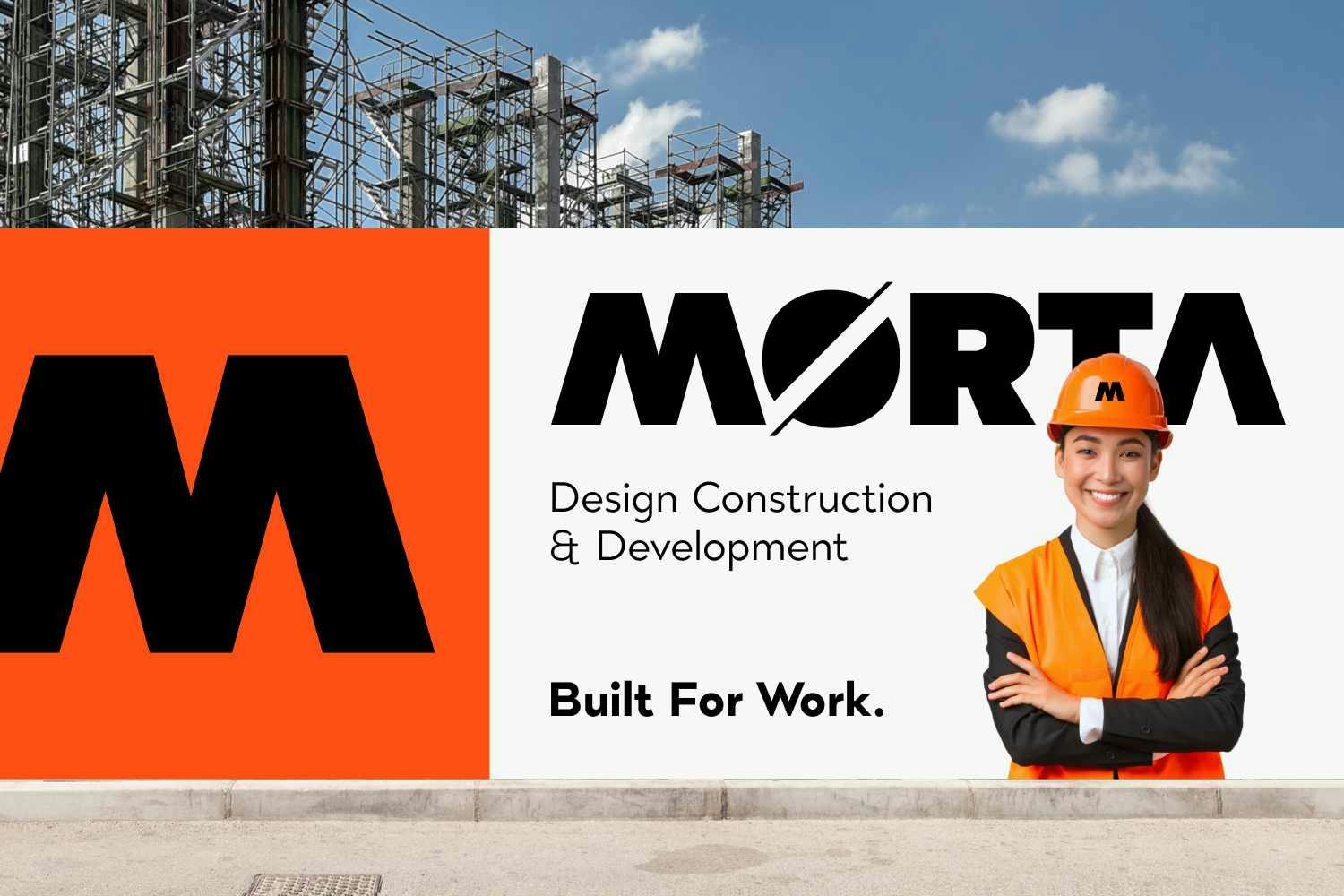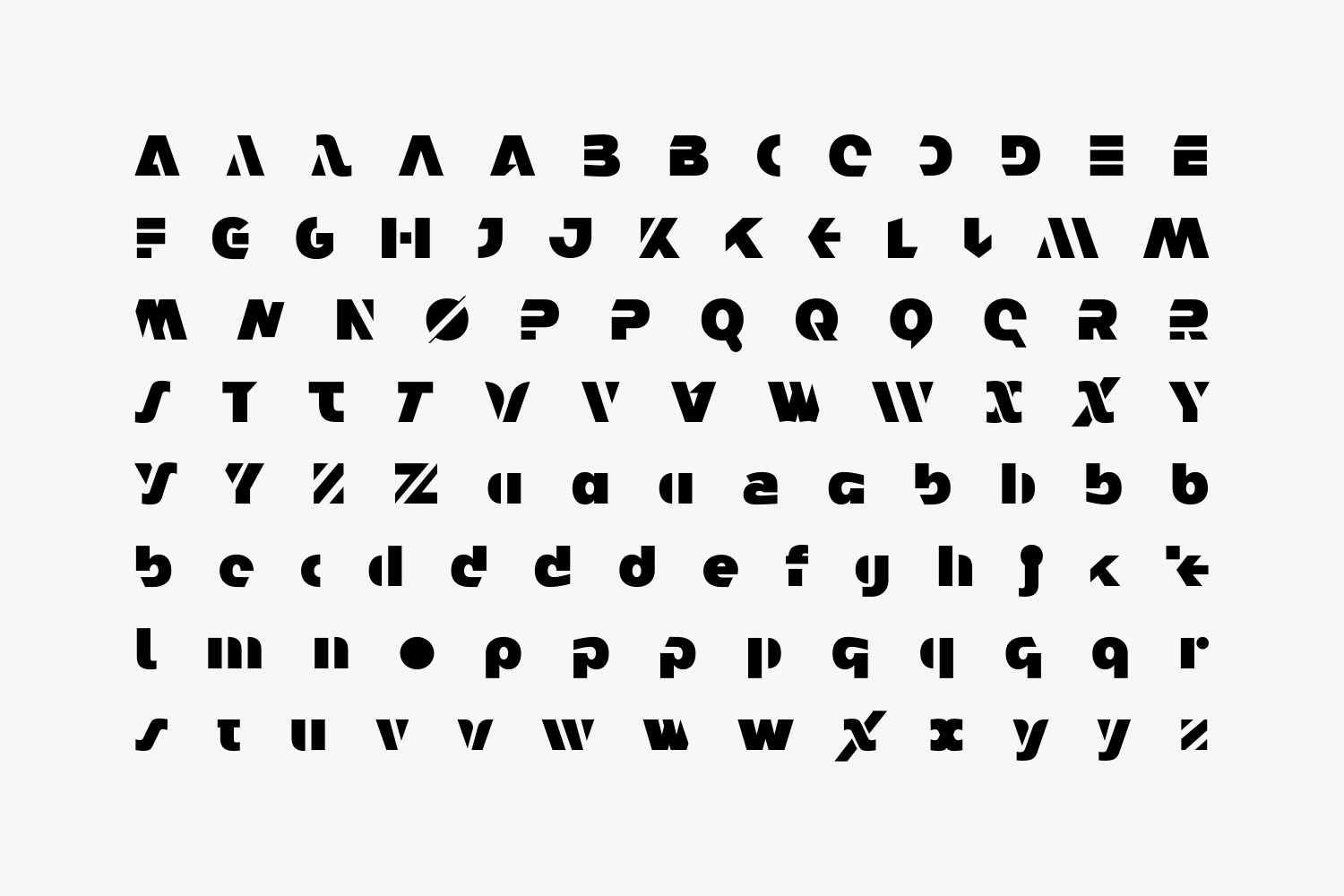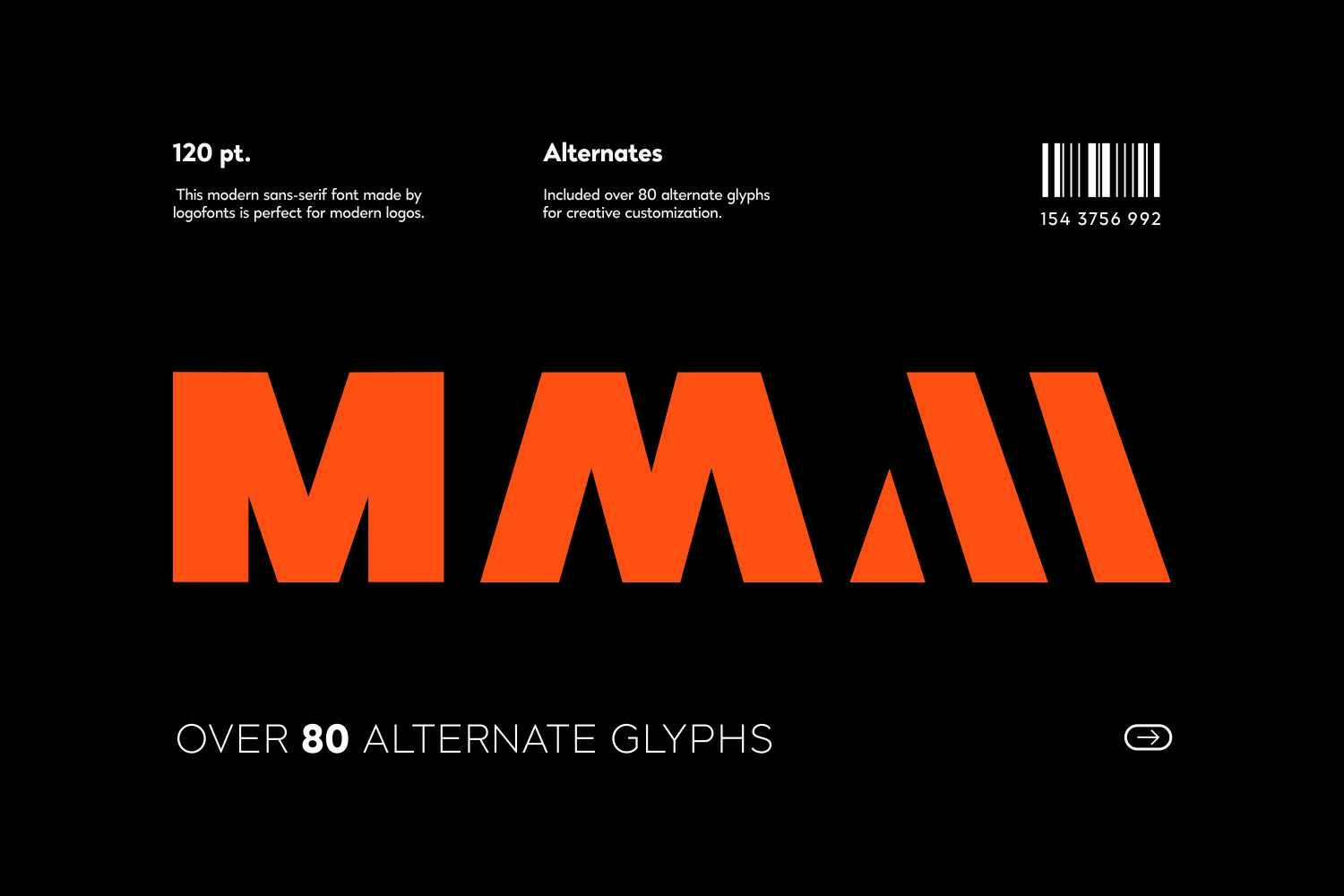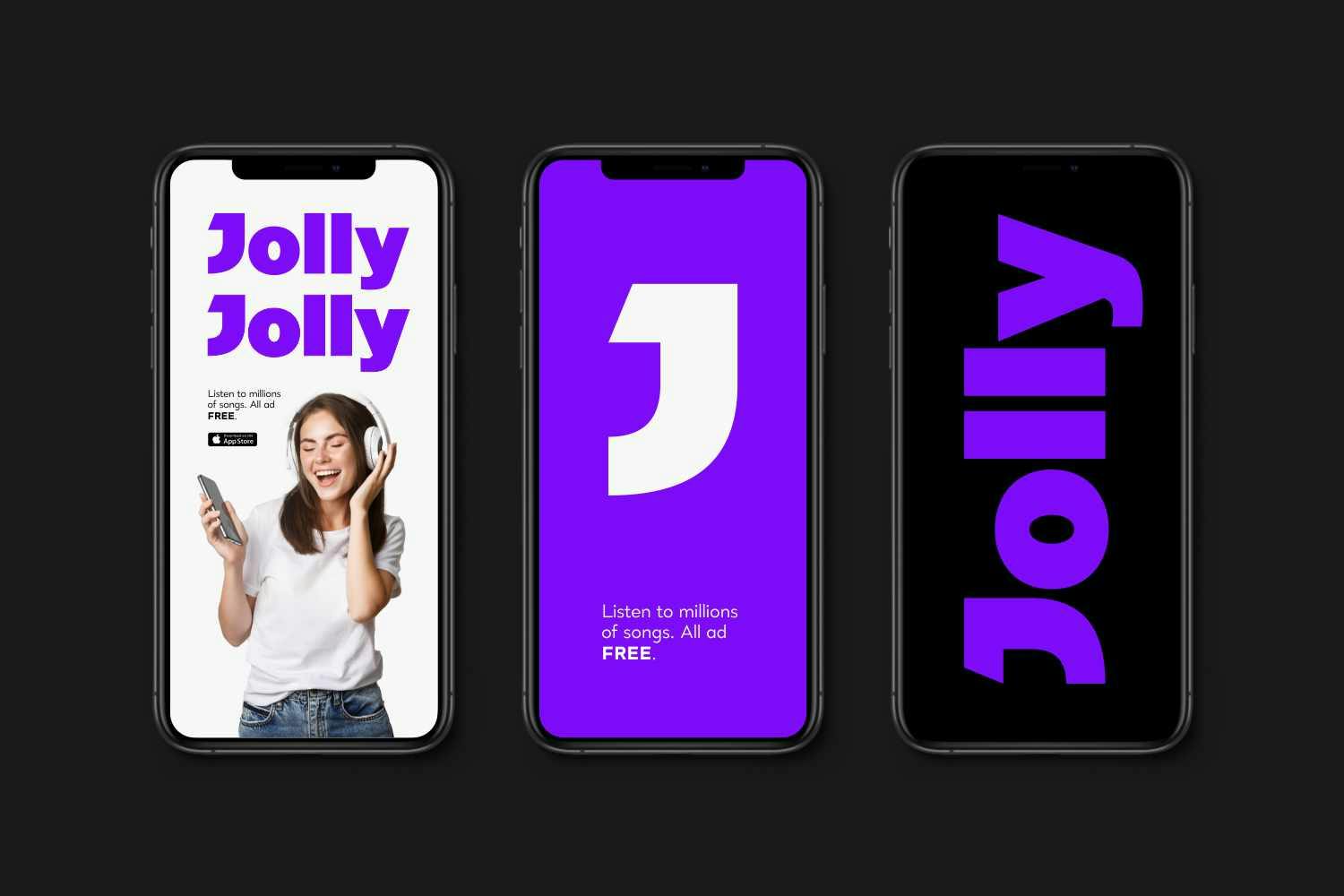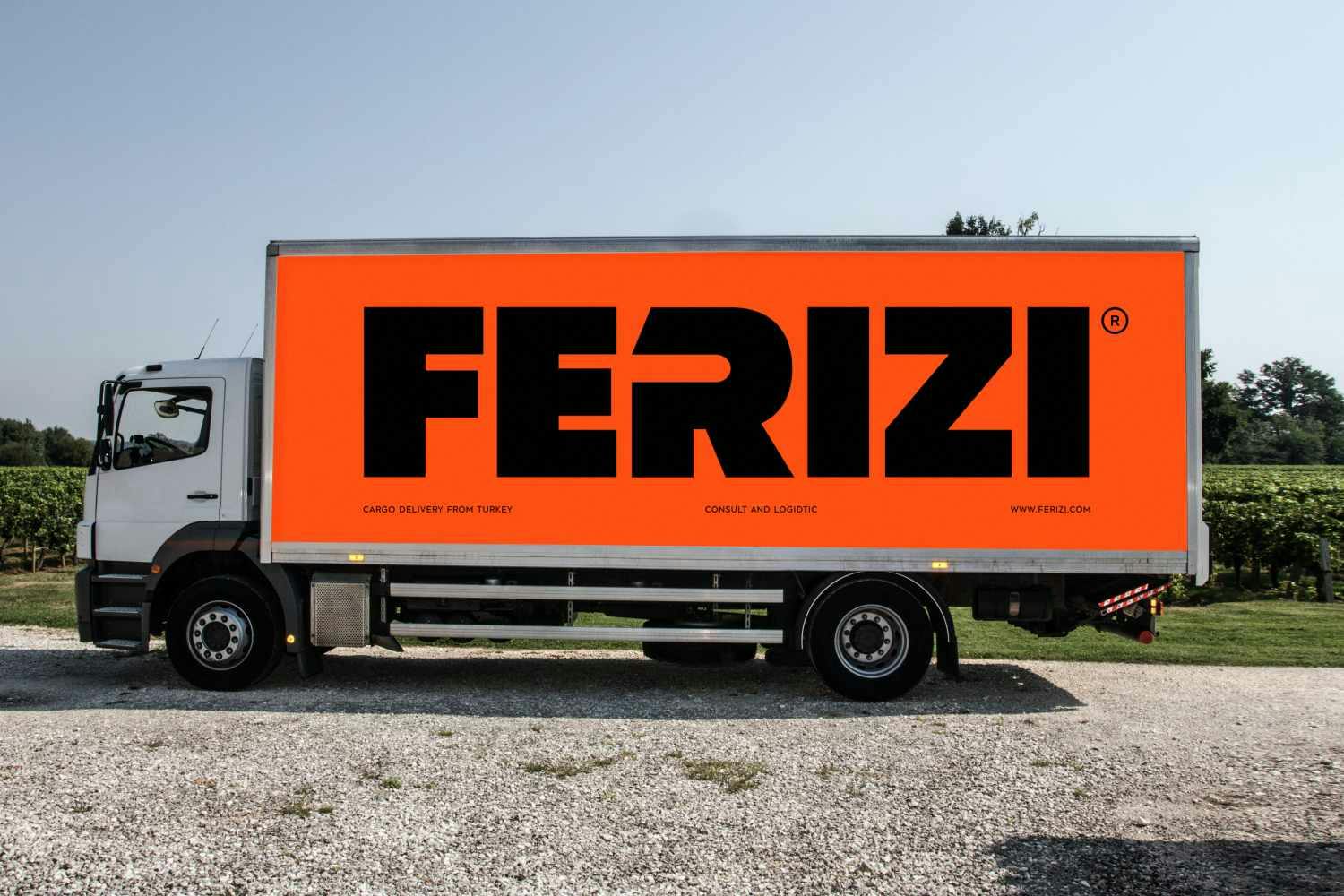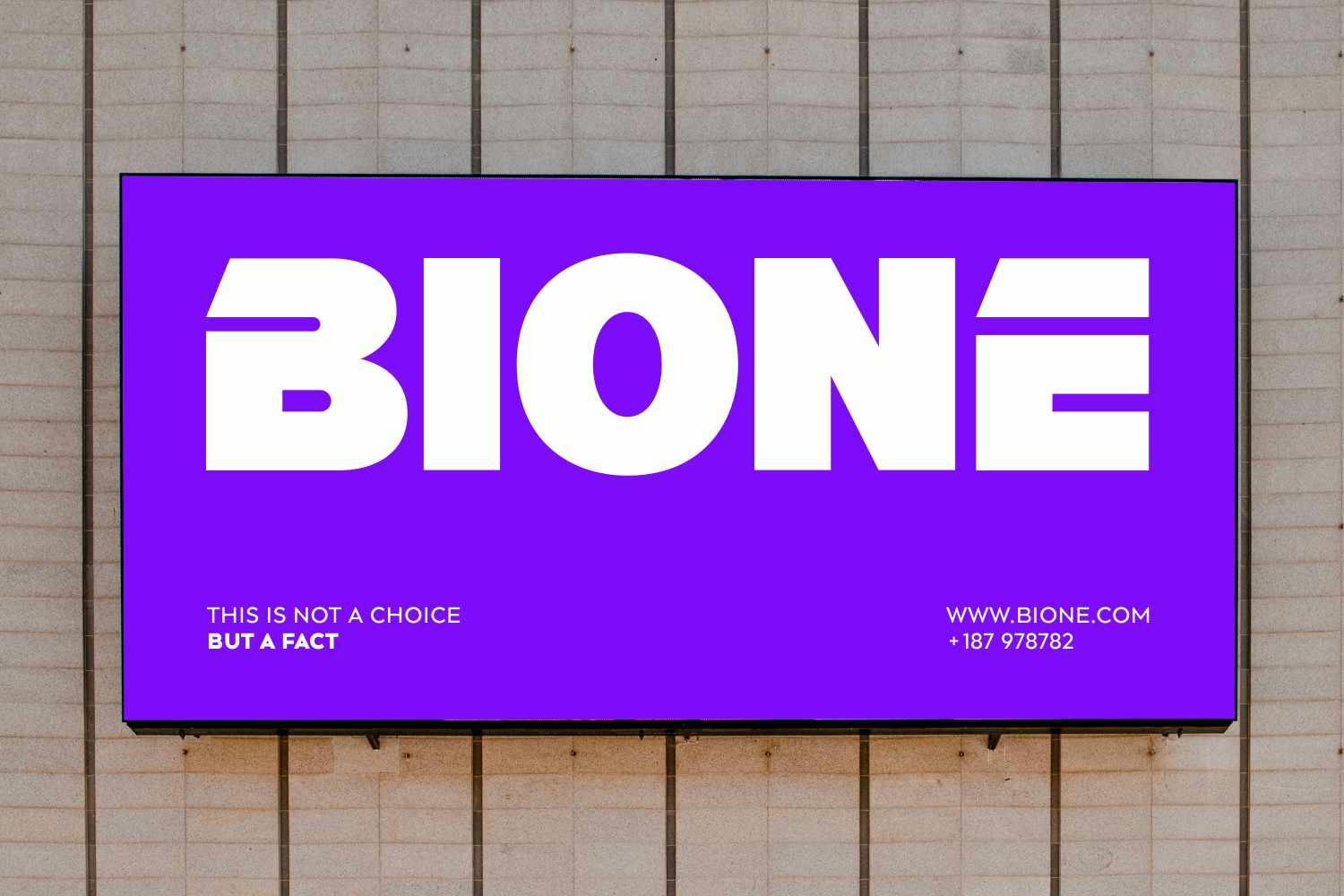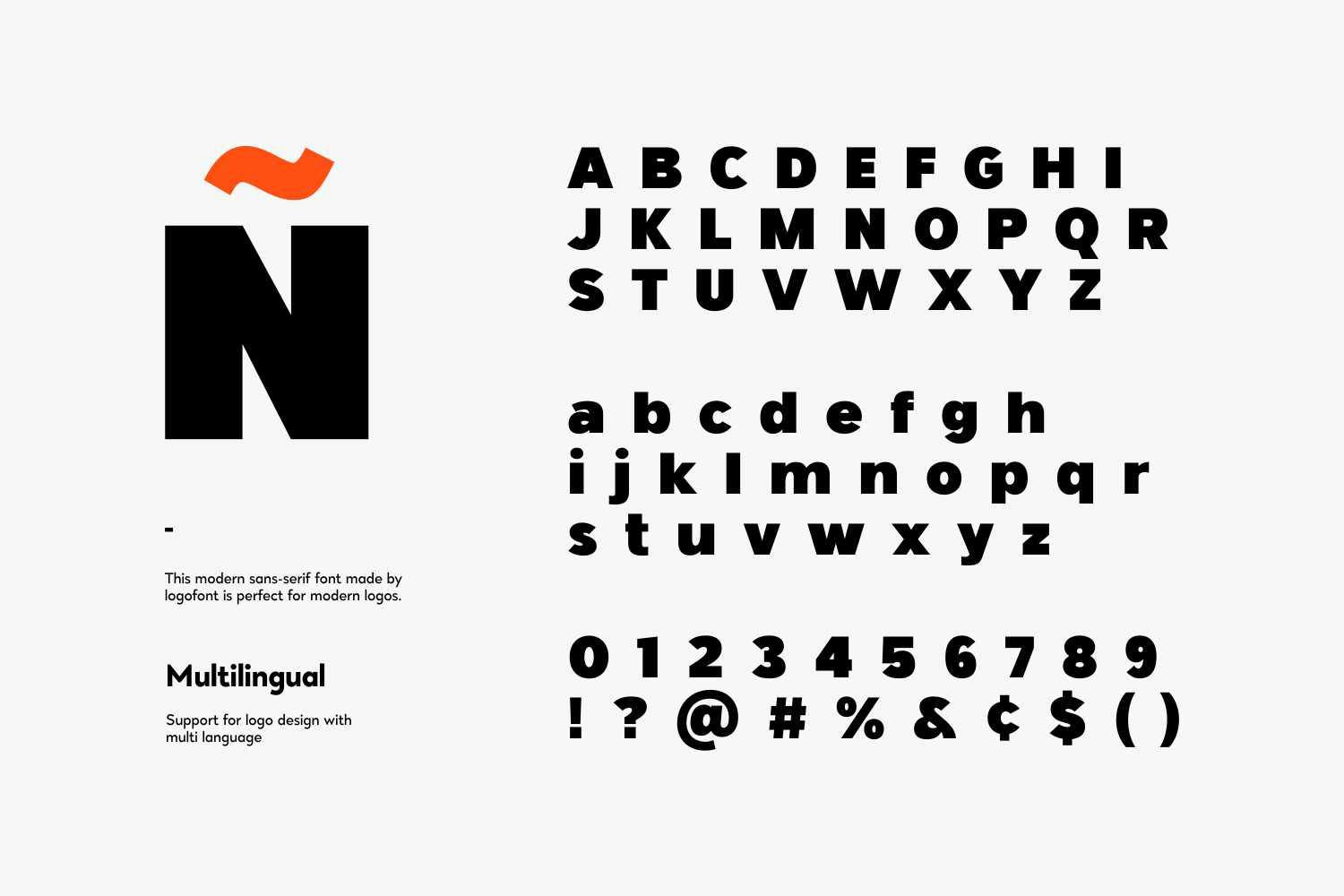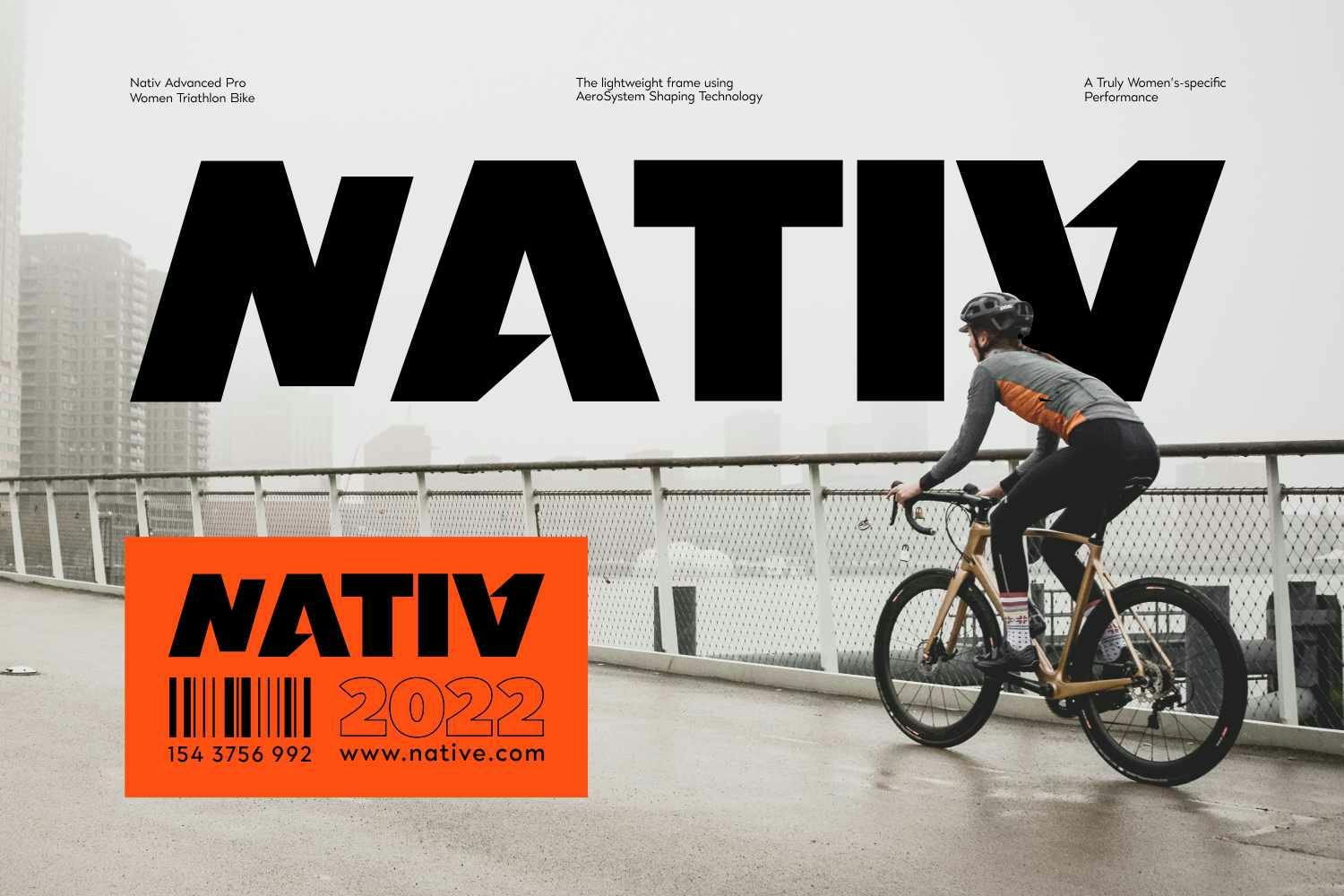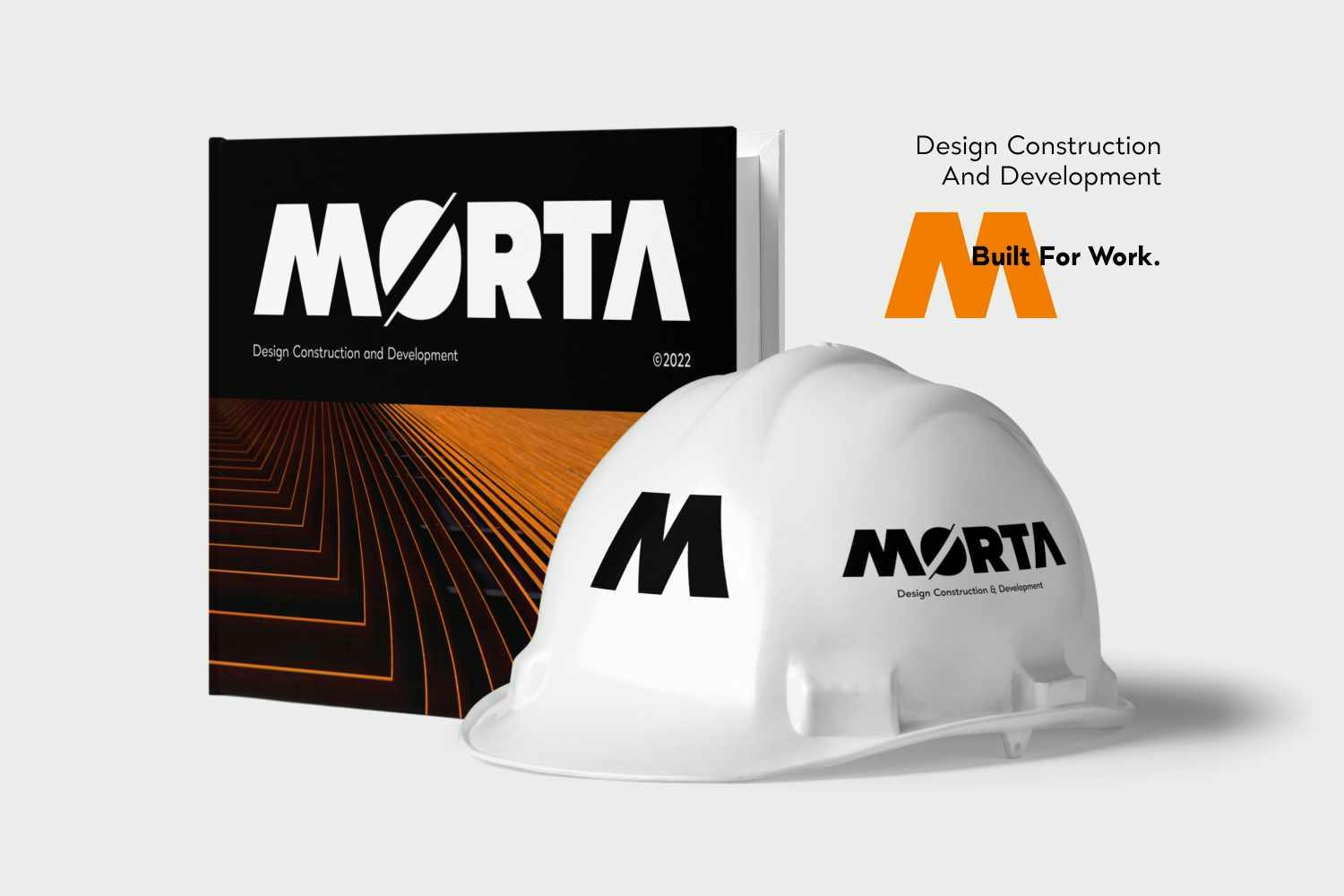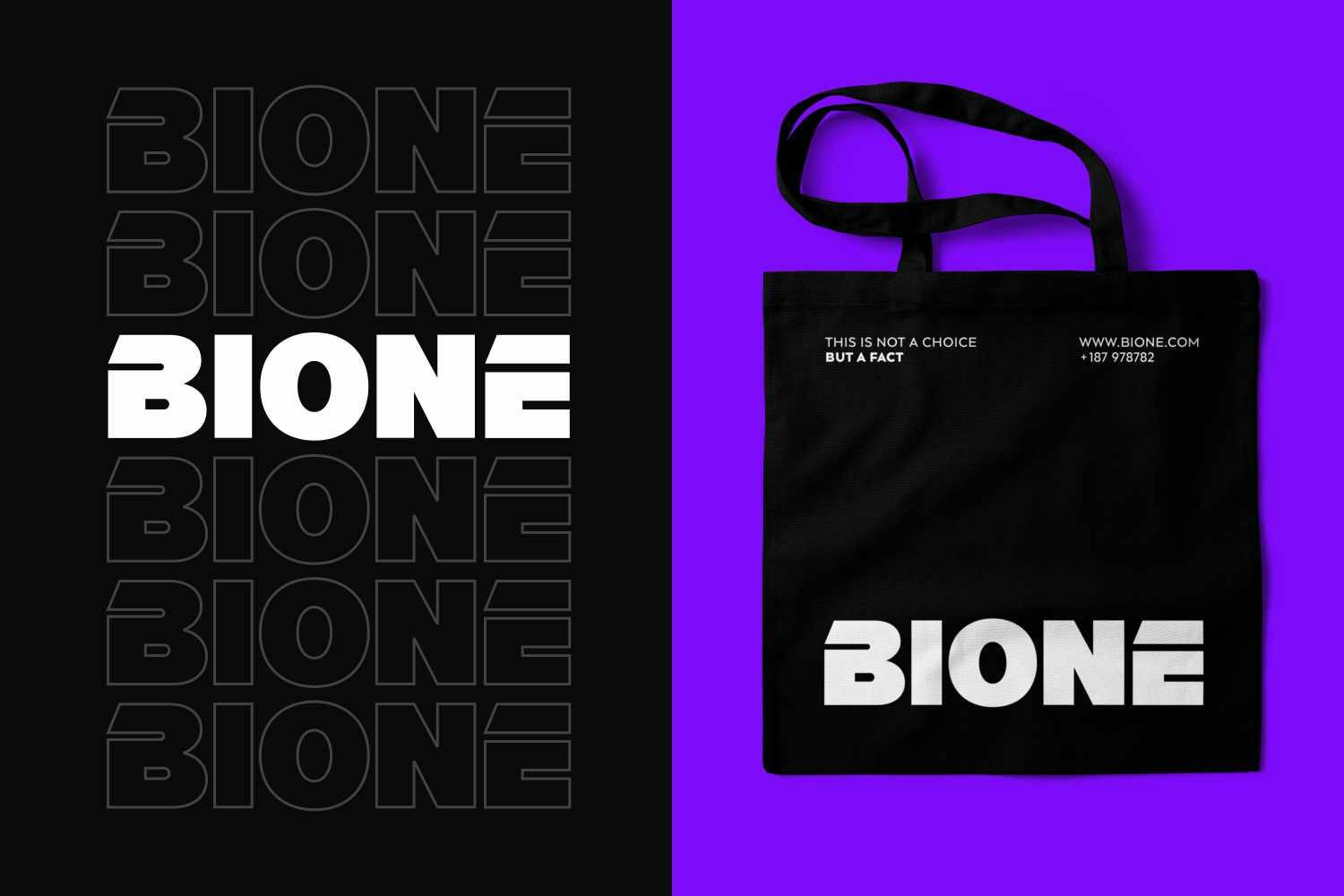
فونت پرو فونت یک فونت سنس سریف است که برای طراحی لوگو محصولات، پوستر، عناوین، لوگو کارت، وبسایت، مجله، بستهبندی، لوازمالتحریر و بسیاری از پروژههای دیگر مناسب میباشد. به سادگی میتوانید با استفاده از این فونت، نوع لوگوی خود را ایجاد کنید. فونت پرو فونت دارای ویژگی Open Type است که دسترسی به مجموعهای بزرگ از حروف جایگزین منحصر به فرد و بسیاری از لیگاتورها را فراهم میکند تا طراحی شما را آسانتر کند.